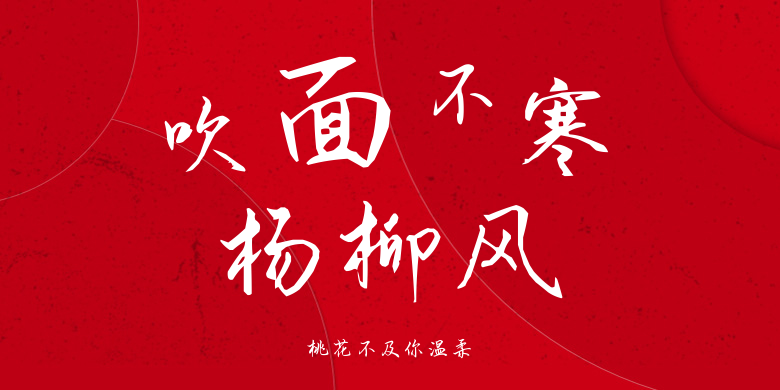
桃花不及你温柔
桃花不及你温柔,这款字体结构工整、笔画清晰,兼顾美观与易读性,适用于标题、正文、海报、包装、LOGO 等多种场景。字形优雅稳定,风格百搭耐看,适配日常排版与创意设计,让文字呈现更舒适、更具质感。桃花不及你温柔一笔一画,皆是细节,以均衡的比例、流畅的线条打造舒适视觉体验,字形端正大气,风格简约现代。无论是商业设计、品牌宣传还是日常排版,都能轻松驾驭,让文字更有格调与力量。桃花不及你温柔字体下载。